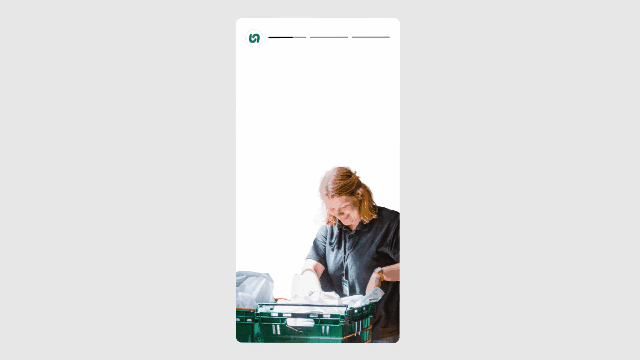
투게더 산스: 트러스셀 트러스트의 리브랜딩
트러스셀 트러스트가 ‘함께’라는 주제로 진행한 리브랜딩은 폰트 하나가 얼마나 큰 변화를 이끌어낼 수 있는지 잘 보여줍니다. 디자이너들과 폰트 전문가들이 협업해 만든 Together Sans는 단순한 글자가 아니라 브랜드 아이덴티티 그 자체로 자리 잡았습니다. 특히 손을 맞잡은 로고는 브랜드의 목표와 메시지를 직관적으로 전달하며, 디자인과 메시지의 균형을 완벽하게 맞췄죠.
투게더 산스: 트러스셀 트러스트의 리브랜딩
영국에서 기아 문제 해결을 목표로 영국에서 활동 중인 자선단체 Trussell Trust(트러스셀 트러스트)가 최근 브랜드 리브랜딩을 단행했습니다. 이번 프로젝트는 디자인 스튜디오 OPX와 폰트 전문 기업 Monotype(모노타입)의 협업으로 진행됐습니다.
리브랜딩 작업은 OPX 스튜디오의 크리에이티브 디렉터 David Bennet(데이비드 베넷), 모노타입의 크리에이티브 타입 디렉터 Emilios Theofanous(에밀리오스 테오파노우스), 이그제큐티브 크리에이티브 디렉터 Phil Garnham(필 가넘)이 함께 이끌었습니다.
트러스셀 트러스트의 브랜드 아이덴티티
이번 리브랜딩의 핵심 주제는 ‘함께(Together)’였습니다. 이 가치를 담아낸 전용 서체 Together Sans(투게더 산스)는 트러스셀 트러스트의 새로운 브랜드 아이덴티티를 시각적으로 표현하는 데 중심적인 역할을 했습니다.
프로젝트를 이끈 데이비드 베넷은 이렇게 설명합니다. “우리는 브랜드를 하나로 묶어줄 중심 개념이 필요했어요. 그리고 그 답은 ‘함께’였죠. ‘함께’라는 단어는 이 브랜드가 지향하는 모든 걸 자연스럽게 담아낼 수 있는 우산 같은 존재였어요.”
전용 폰트와 로고
디자인팀은 트러스셀 트러스트가 지향하는 ‘함께하는 마음’과 ‘서로 돕는 정신’을 담아내기 위해 새로운 전용 폰트를 만들었습니다. 이 따뜻한 메시지는 로고에도 잘 드러납니다.
새 로고에는 손을 맞잡은 모습이 들어가 있는데, 이 이미지는 Trussell Foodbanks(트러스셀 푸드뱅크)의 머리글자인 ‘T’와 ‘F’를 동시에 표현한 것입니다. 에밀리오스 테오파노우스는 “이 폰트는 구조적으로 안정감이 있으면서도, 사람 냄새 나는 따뜻함을 함께 담고 있어요.”라고 설명했습니다.
“폰트 하나로도 놀라운 변화를 만들 수 있습니다.”
– 데이비드 베넷
협업의 여정
이번 리브랜딩은 다양한 사람들이 힘을 모아 하나의 목표를 이뤄낸 좋은 예였습니다. 데이비드 베넷은 “스튜디오에 있는 모든 디자이너가 함께 참여해 브랜드의 새로운 모습을 만들어냈어요”라고 말했습니다.
모노타입에서도 에밀리오스 테오파노우스와 필 가넘이 폰트 디자인을 중심으로 긴밀하게 협력했습니다. 필 가넘은 “로고타입은 브랜드의 가치를 보여주면서도, 동시에 안정감과 신뢰를 줄 수 있어야 해요. 그래서 그 균형을 잡는 게 정말 중요했죠”라고 설명했습니다.
이렇게 디자인과 메시지 사이의 균형을 잘 맞춘 덕분에, 새 브랜드는 누구에게나 친근하면서도 믿을 수 있는 인상을 줄 수 있게 됐습니다.
종합적 리브랜딩
이번 리브랜딩은 단순히 새 폰트를 만든 것이 아니라, 브랜드 전체를 새롭게 다듬는 작업이었습니다. 로고, 아이콘, 사진, 색상까지—보이는 모든 요소가 함께 바뀌었죠. 데이비드 베넷은 “기본 방향만 잘 잡히면, 모든 게 자연스럽게 연결돼요. 그 중심엔 늘 폰트가 있고요”라고 말했습니다.
이렇게 브랜드 전체를 하나의 흐름으로 정리한 덕분에, 트러스셀 트러스트가 전하고 싶은 메시지와 가치가 모든 디자인에 잘 담겼습니다. 새롭게 바뀐 모습은 단순히 예뻐진 게 아니라, 사람들에게 ‘우리는 함께한다’는 따뜻한 느낌을 주고, ‘식량 불안을 없애자’는 단체의 목표를 더 확실하게 전달하게 됐습니다.
타이포그래피의 영향력
필 가넘은 “타이포그래피는 브랜드 전반에 감정을 불어넣는 역할을 해요”라며 그 중요성을 강조했습니다. 이번 프로젝트는 폰트 하나가 단순한 디자인 요소를 넘어서, 브랜드의 성격을 만들고 메시지를 효과적으로 전달하는 데 얼마나 큰 역할을 할 수 있는지를 잘 보여줬습니다.
“타이포그래피는 모든 것에 걸쳐 시각적 감성을 전달할 수 있습니다.”
– 필 가넘
트러스셀 트러스트의 리브랜딩은 서체 하나가 브랜드 전체에 얼마나 큰 영향을 줄 수 있는지를 잘 보여줍니다. 데이비드 베넷이 말했듯이, “폰트 하나로도 놀라운 변화를 만들 수 있습니다.”
이번 프로젝트를 통해 트러스셀 트러스트는 단순히 보기 좋은 디자인을 넘어, ‘지원’과 ‘함께’라는 핵심 가치를 진심으로 담아낸 브랜드로 거듭났습니다. 꼼꼼한 디자인과 긴밀한 협업이 만들어낸 이 변화는 타이포그래피가 가진 힘을 다시 한 번 느끼게 해줍니다.